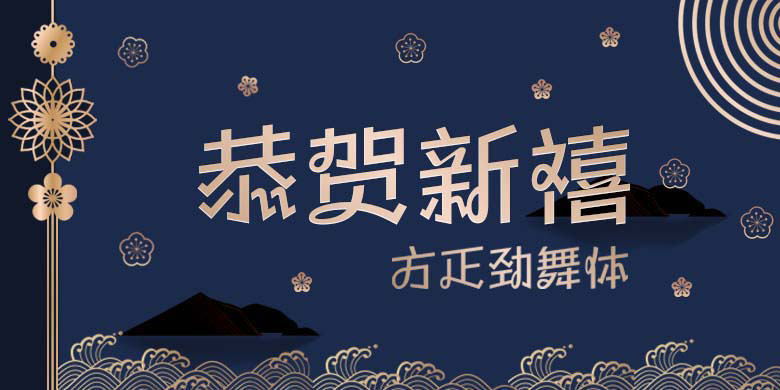
方正劲舞体系列
品牌:方正字库设计师:郭炳权发行时间:2018字库编码:大陆简体(GB2312-80)、简繁扩展(GBK)分类:创意字体
方正劲舞体系列
方正劲舞体,该款字体参考了行书基础结构进行创意设计,融入了黑体的简洁,造型特异,充满现代感。撇、捺间带有明显的折角,凸显该字体的简洁有力的个性,字体带有蜷曲的装饰性饰角,其风格隽秀大方,适用于商业广告以及包装设计当中。